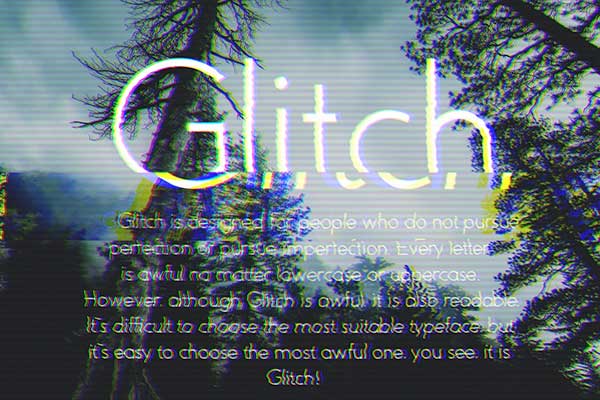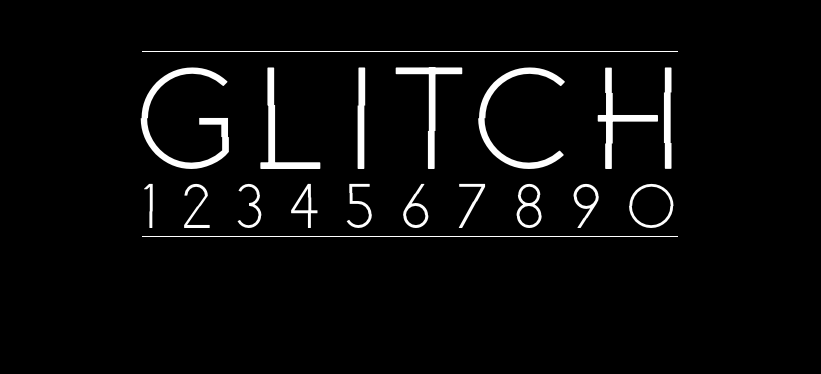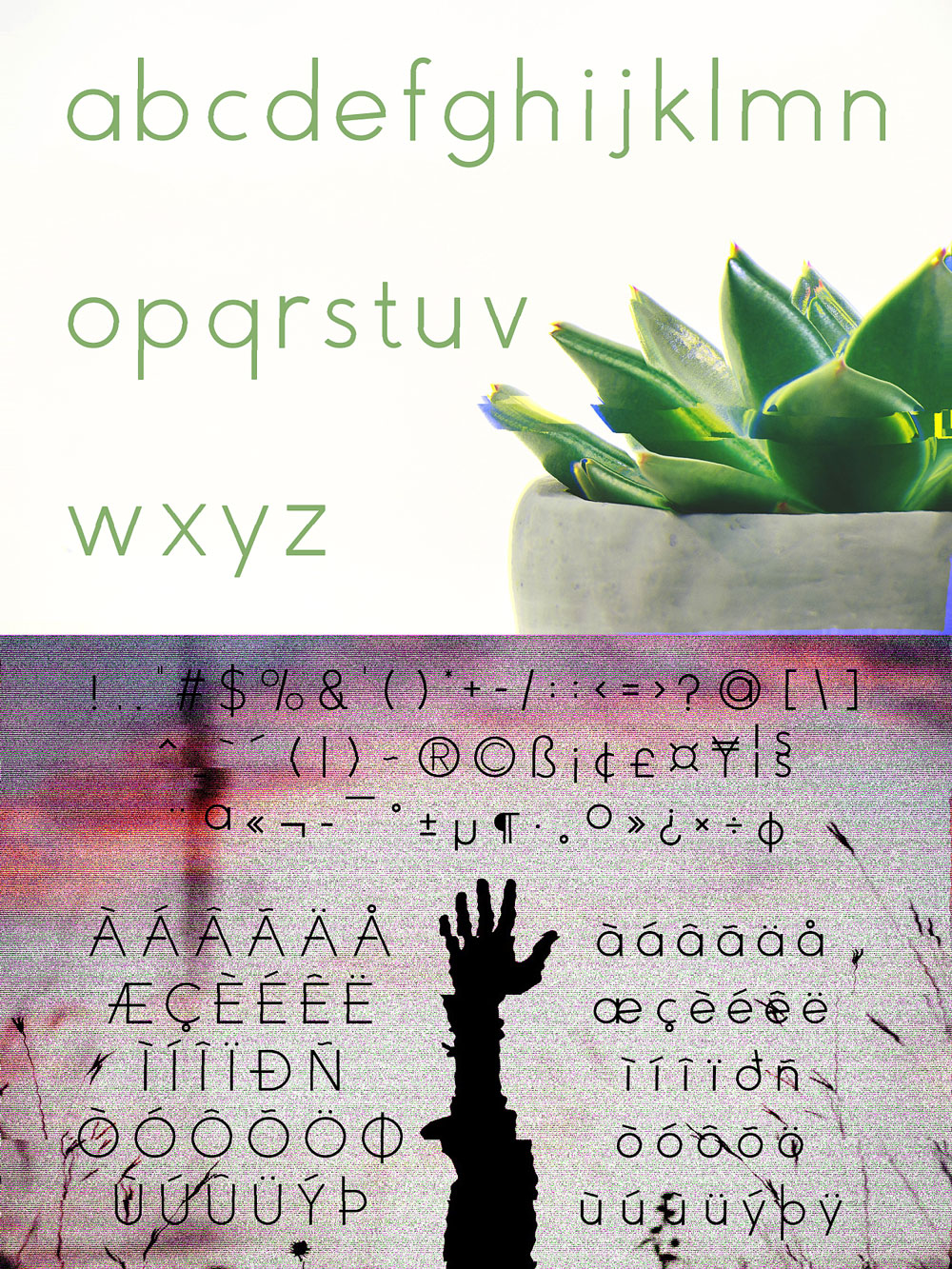
Glitch
Glitch字体是南京的学生“咋够”创作的一款英文字体,这是一款为不追求完美和追求不完美的人们设计的字体。每一个字母,无论小写还是大写都被设计得不完美。
该字体在字形上刻意加入了一些错位,营造抖动和错觉;作者自言尽管是设计得不完美的字体,但是其可读性却不错。想要找到最适合的完美字体是一件十分困难的事,何不尝试使用最不完美的字体呢?